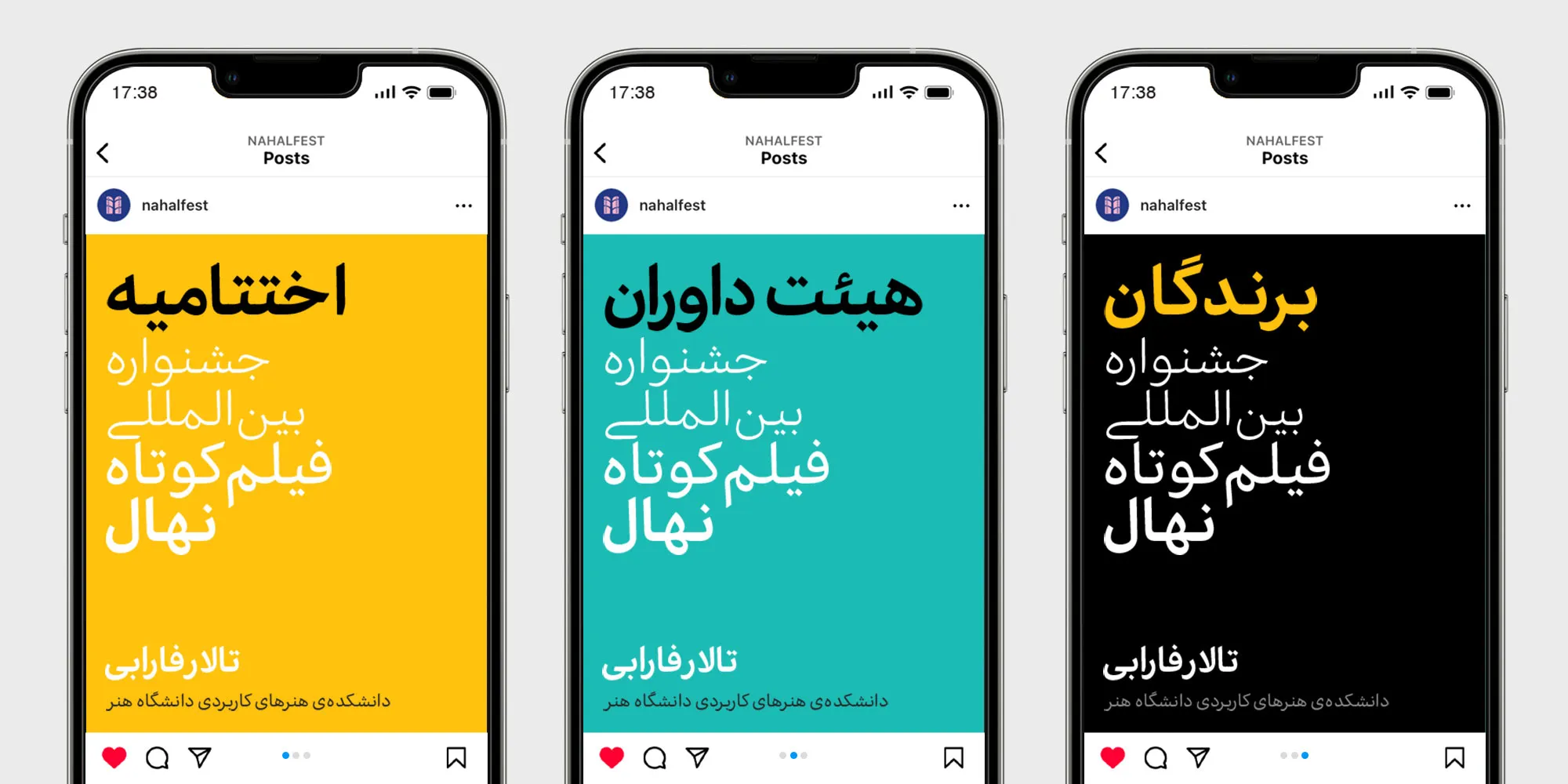
معرفی و دانلود ۵ فونت ترکیبی ثلث، نسخ و نستعلیق
خوشبختانه امروزه فضای تایپ فارسی به لطف طراحان مختلف قلم، در شرایط خوبی بوده و اکنون میتوان در سبکهای مختلف چندین فونت را در اختیار داشت که بهشکل ترکیبی یا تکی از آنها استفاده کرد. سبک ثلث، نسخ و نستعلیق جزو محبوبترین سبکها هستند که که از دیرباز موجب خلق فونت های جدید متعددی شدهاند.
به همین جهت در ادامه این مقاله از وبلاگ فونتچی به معرفی ۵ فونت ترکیبی سبک ثلث، نسخ و نستعلیق خواهیم پرداخت که اساس آنها بر پایه یکی از این سبکها بوده، اما با تلفیقی از سایر سبکها، بهشکل مدرن و امروزی در آمدهاند.
این نوع سبک فونتها در کارهای گرافیکی، خصوصا مواردی که جنبه تبلیغاتی داشته یا قرار است در شبکههای اجتماعی بهمنظور معرفی برند مورد استفاده قرار گیرد، بیشتر مورد استفاده قرار میگیرند. هر یک از قلمهایی که در این سبک هستند، نشانگر اصالت برای برند شما خواهند بود.
اینکه از کدامیک از فونتهای ثلث و نستعلیق استفاده کنید، بستگی به این دارد که قرار است با چه هدفی از آنها استفاده کنید. برخی برای صنعت مد و پوشاک ساختاری عالی و بهروز به نوشتههای شما خواهد داد که تفاوتی ندارد از آن برای تبلیغات استفاده کنید، یا اینکه در نسخه وب برای بخشهایی همچون اسلایدرهای تبلیغاتی مورد استفاده قرار گیرد.
برخی دیگر نیز برای استفاده در تبلیغات محیطی یا بستهبندی محصولات مناسب هستند که میتوانید از آنها کمک بگیرید. این موضوع کاملا به سلیقه شما در طراحی و تجربیات حوزه کاریتان بستگی دارد. در ادامه ضمن معرفی این فونتها، مثالهایی از هر صنعت برای آنها ذکر خواهیم کرد.
فونت دوران با ۶ وزن
فونت دوران را به عنوان اولین فونت ترکیبی ثلث و نستعلیق معرفی کرد که بسیار سر و صدا به پا کرد. این قلم با ساختار با اصالتی که در قلب خود از این دو سبک جایداده، اما در عین حال کاملا به شکل امروزی، مدرن و دوستانه طراحی شده است.
به عقیده طراح این فونت، «فرشته ایرانشاهی»؛ صنعت مد و پوشاک با این فونت تحت تاثیر قرار گرفته که در این مورد هم موفق بوده است. در بسیاری از فروشگاههای اینترنتی که در زمینه لباس، کیف و کفش فعالیت دارند از این فونت بهمنظور تبلیغ محصولات، اسلایدر و تصاویر گرافیکی استفاده میشود که به معرفی بهتر محصول کمک شایانی کرده است.
فونت دوران در ۶ وزن طراحی شده که شامل نسخه نازک تا خیلی ضخیم است. تمامی این وزنها هم در قالب یک فونت مجتمع از نسخه وریبل پشتیبانی میکنند که متغیرهای تغییر وزن و حروف جایگزین را در خود دارد.
از این فونت جسور میتوانید برای فونت عناوین و متون استفاده کنید. اما توصیه میشود که برای متنهای کوتاه مورد استفاده قرار گیرد که در وزنهای سنگینتر با ابعاد بزرگ خود را بهتر نشان خواهد داد. استفاده از این فونت بهعنوان فونت متون طولانی به دلیل خوانایی نسبتا خسته کنندهای که خواهد داشت توصیه نمیگردد.
فونت وریبل ابر با ۳ سبک
ابر فونت دیگری است که ساختاری نزدیک به همان دو ترکیب را دارد. اما با اینحال بر اساس خط نسخ طراحی شده و چیدمان حروف و زوایای بهگونهای است که تا حدودی میتوان آثاری از نستعلیق و ثلث را نیز به سختی در آنها پیدا کرد. البته به شرطی که تمامی سبکها مورد بررسی قرار گیرد.
این فونت از ۳ سبک خاص برای تایپ بهره میبرد که شامل پایین، متوسط و بالا است. هرچه این سطوح افزایش پیدا میکند، ساختار فونت ضمن اینکه نرمتر میشود، زوایا و ضخامت حروف در ابتدا و انتها نیز تغییر میکند. در عین این نوک سبک نمایشی، فونت ابر از نسخه وریبل پشتیبانی کرده و مجموعا شامل ۱۵ وزن در قالب این ۳ سبک است.
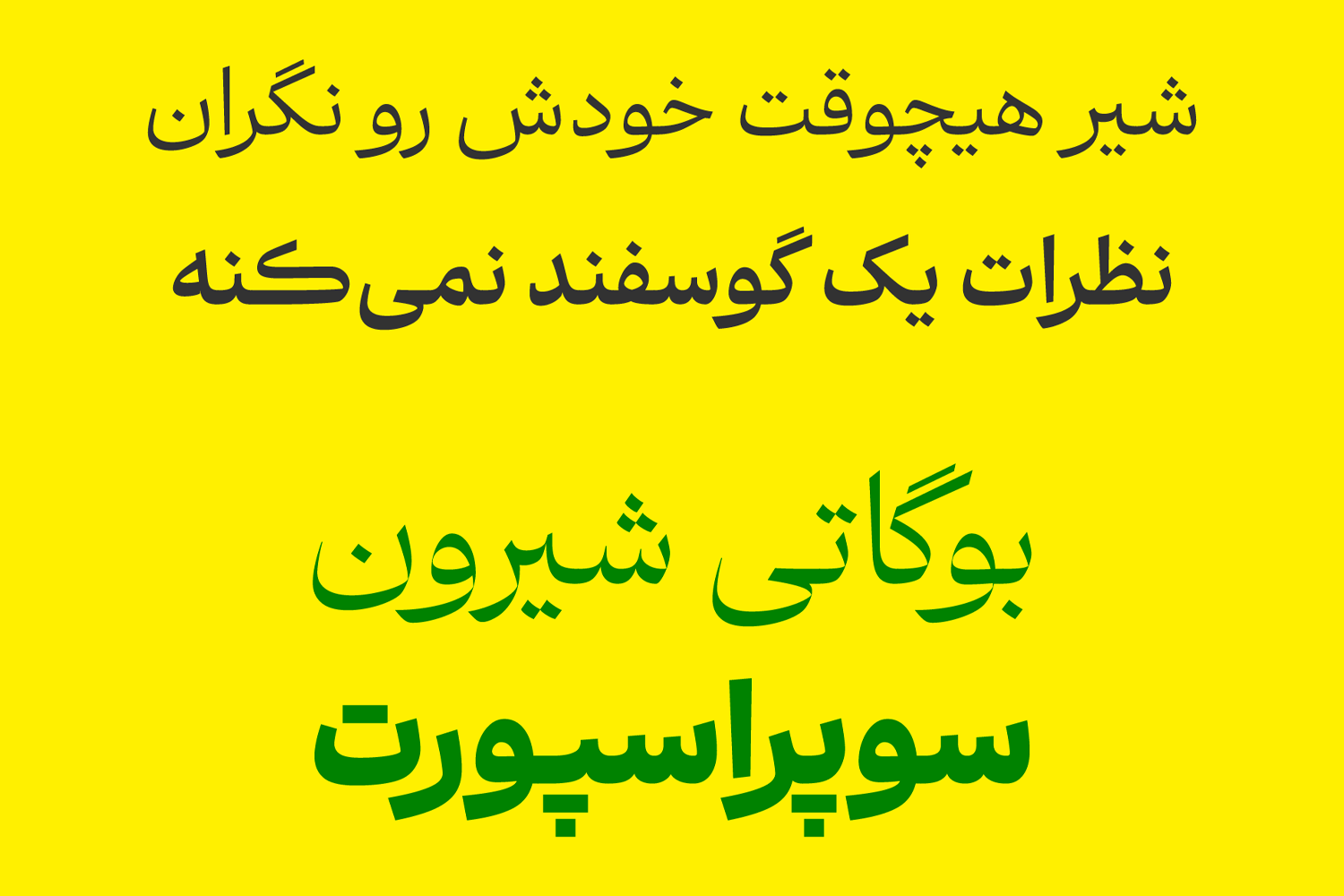
این فونت جدای از اینکه در تبلیغات بسیار هوشمندانه و زیبا بهنظر میرسد، برای استفاده در فونت وبسایت نیز مناسب است. حروف جایگزینی که این فونت در هر یک از این سبکها در اختیار قرار میدهد دست شما را برای طراحی بازتر میکند تا آثار گرافیکی خارقالعادهای خلق کنید.
فونت هستی با دو استایل
فونت هستی نیز با توجه به ظاهری که در خروجی خود دارد به شکل کاملا نستعلیق به نظر میرسد؛ اما این در حالی است که از سبک تماما نسخ برای طراحی آن استفاده شده، اما به منظور نمایشی کردن آن، ساختاری شبیه به نستعلیق امروزی روی آن اعمال شده است.
این فونت توسط مسلم ابراهیمی که جزو پرکارترین طراحان فونت فارسی است ارائه شده است که هنوز در نسخههای اولیه بوده و شامل امکانات محدودی است. اما طبق گفته طراح، قرار است نسخههای وریبل و سبکهای جدید بهمرور زمان با توجه به استفادهای که کاربران از این قلم دارند به آن افزوده شود.
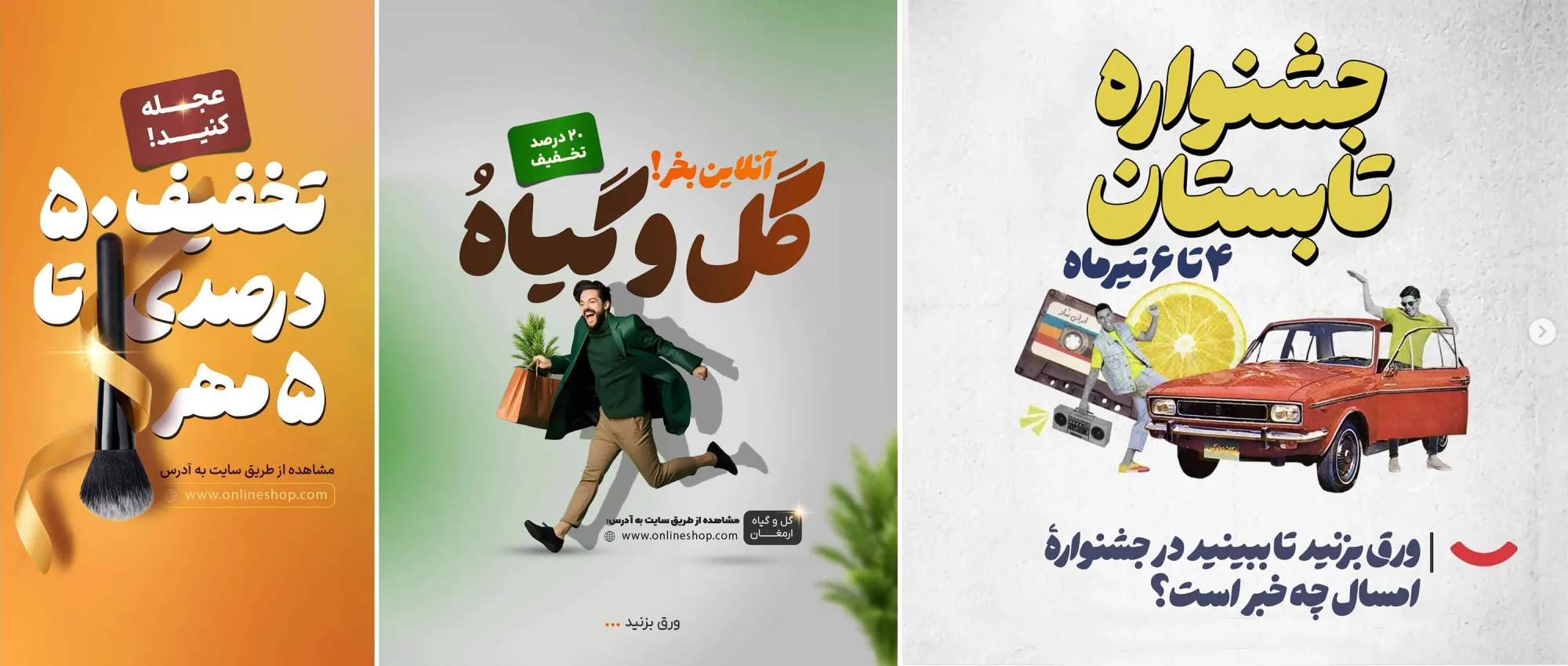
فونت هستی دارای ظاهری کاملا بولد و ضخیم است که شامل یک وزن سنگین (Heavy) است. به منظور نمایشیتر کردن یک نسخه با نام HeavyRD برای آن در نظر گرفته شده که حالت گرد و اصطلاحا نرم فونت را شامل میشود که نقطهها دارای سبک گرد به جای گوشهای هستند.
از این فونت میتوانید در کارهایی که جنبه تبلیغاتی و فرهنگی دارد بیشترین استفاده را ببرید. یکی از پرکاربردترین صنایع برای این قلم بستهبندی محصولاتی است که در حوزه فرهنگ و هنر، خوراک و محصولات نوشتافزار باشد. این فونت در چنین محصولاتی بیانگر زیبایی، اصالت و جاهطلب است.
فونت نسخ پیکان با ۶ وزن
فونت پیکان دیگر اثری است که بر پایه خط نسخ طراحی شده است. این فونت یادآور آثار چاپی دهههای ۴۰ تا ۶۰ شمسی است که در روزنامهها گاها فونتهایی شبیه به آن دیدهایم. اما با این تفاوت که ظاهر حروف بهطور ناگهانی دگرگون شده و ساختاری نمایشی به خود گرفته است.
فونت پیکان در ۶ وزن ارائه شده است که از نسخه وریبل نیز پشتیبانی میکند. در ساختار این فونت ظاهر حروف در بخشهای کاملا ضخیم و در عین حال در چشمیها، ابتدا و انتهای حروف به شکل ناگهانی نازک شده است؛ طوری که ظاهری کاملا تیز و برنده دارد.
این فونت که از طرههای تزئینی در برخی حروف دارای خطوط قائم پشتیبانی میکند، مناسب فونت عناوین است. میتوانید در صنایع چاپ از این قلم استفاده کنید که جنبه خبری داشته یا اینکه به منظور تبلیغات مورد استفاده قرار گیرد.
برای اینکه جای خالی یک فونت ترکیبی برای قلمهای معرفی شده را پر کنیم، فونت اکران را بر پایه خط سنس معرفی کردهایم که برای متون بلند میتوانید از آن استفاده کنید. این فونت با اینکه ظاهری کاملا متفاوت به سایر قلمها دارد، اما با قرارگیری در کنار آنها میتواند مکمل نوشتههای شما باشد.